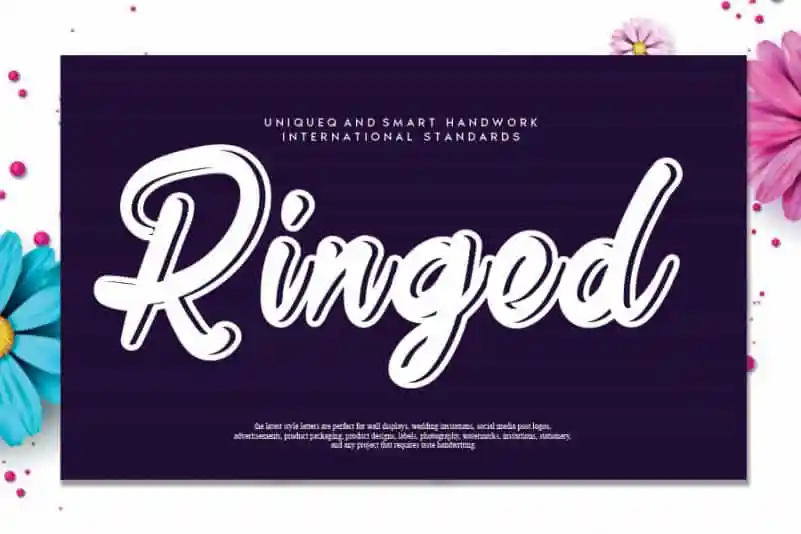
Ringed Script Font – Download Grátis
A fonte ‘Ringed Script Font’ é uma exquisite handwritten font que transmite classismo ao mesmo tempo que exala contemporaneidade e frescura. Ideal para projetos que buscam um toque elegante, esta fonte manufaturada pelo designer andikastudio mantém suas influências de escrita a lápis enquanto se apresenta como moderna e atual. É perfeita para quem busca uma personalização única em seus designs digitais – ela é capaz de dar vida ao seu trabalho, levando-o a um novo patamar. Seja você um amante da arte digital ou simplesmente alguém que aprecia uma maneira sofisticada e inovadora de expressar sua criatividade, ‘Ringed Script Font’ é definitivamente para você.